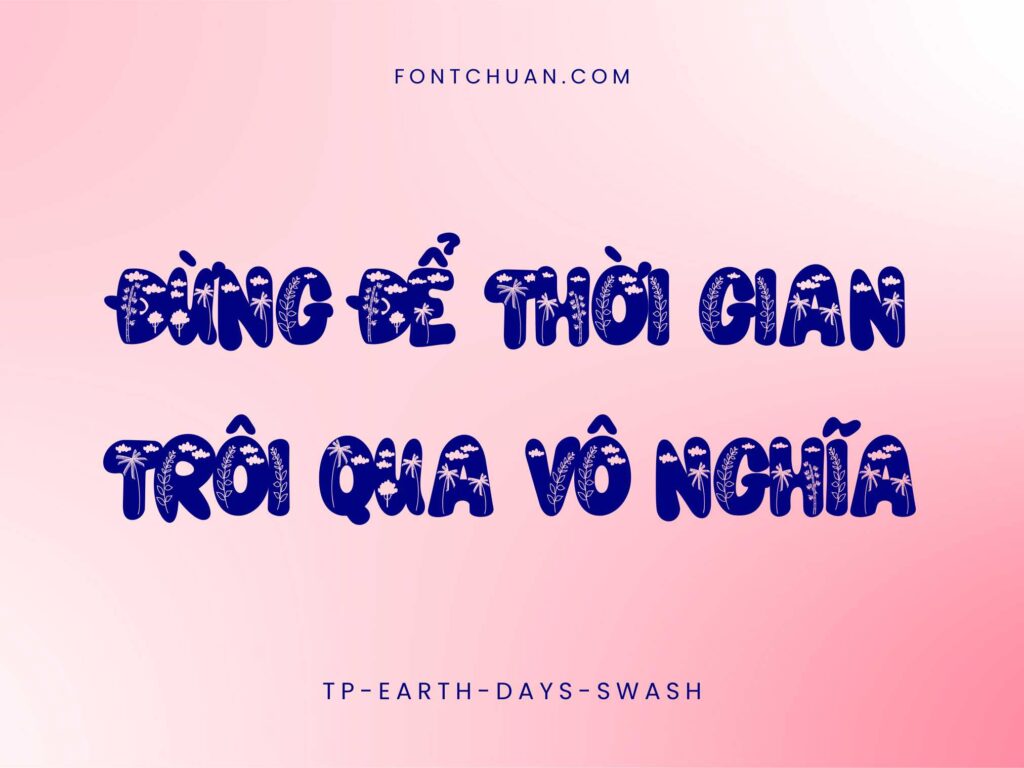
Font TP Earth Days Swash Việt Hóa
Tác giả Font: Letterara
Earth Days Swash là một Font chữ quảng cáo mang phong cách trang trí độc đáo, lấy cảm hứng từ Ngày Trái Đất, mang đến cảm giác vui tươi và đáng yêu. Thiết kế của font này bao gồm các ký tự tròn trịa, ngộ nghĩnh và giàu sức biểu cảm, tạo nên sự thân thiện và thu hút cho các dự án thiết kế. Font đã được Việt hóa để hỗ trợ tiếng Việt bởi Tuỳn Pucca, giúp mở rộng phạm vi ứng dụng cho người dùng Việt Nam. Đây là một trong những font được thành viên Font Chuẩn sưu tầm và chia sẻ nhằm đáp ứng nhu cầu đa dạng trong thiết kế thương hiệu và truyền thông quảng cáo.
Đặc điểm thiết kế của Earth Days Swash bao gồm các nét chữ đậm và tròn, tạo cảm giác vui nhộn và thân thiện. Font này phù hợp cho các ứng dụng như sách thiếu nhi, thương hiệu vui tươi, thiệp mời dự tiệc và poster không chính thức. Các ngành nghề phù hợp bao gồm giáo dục, giải trí và thiết kế đồ họa.